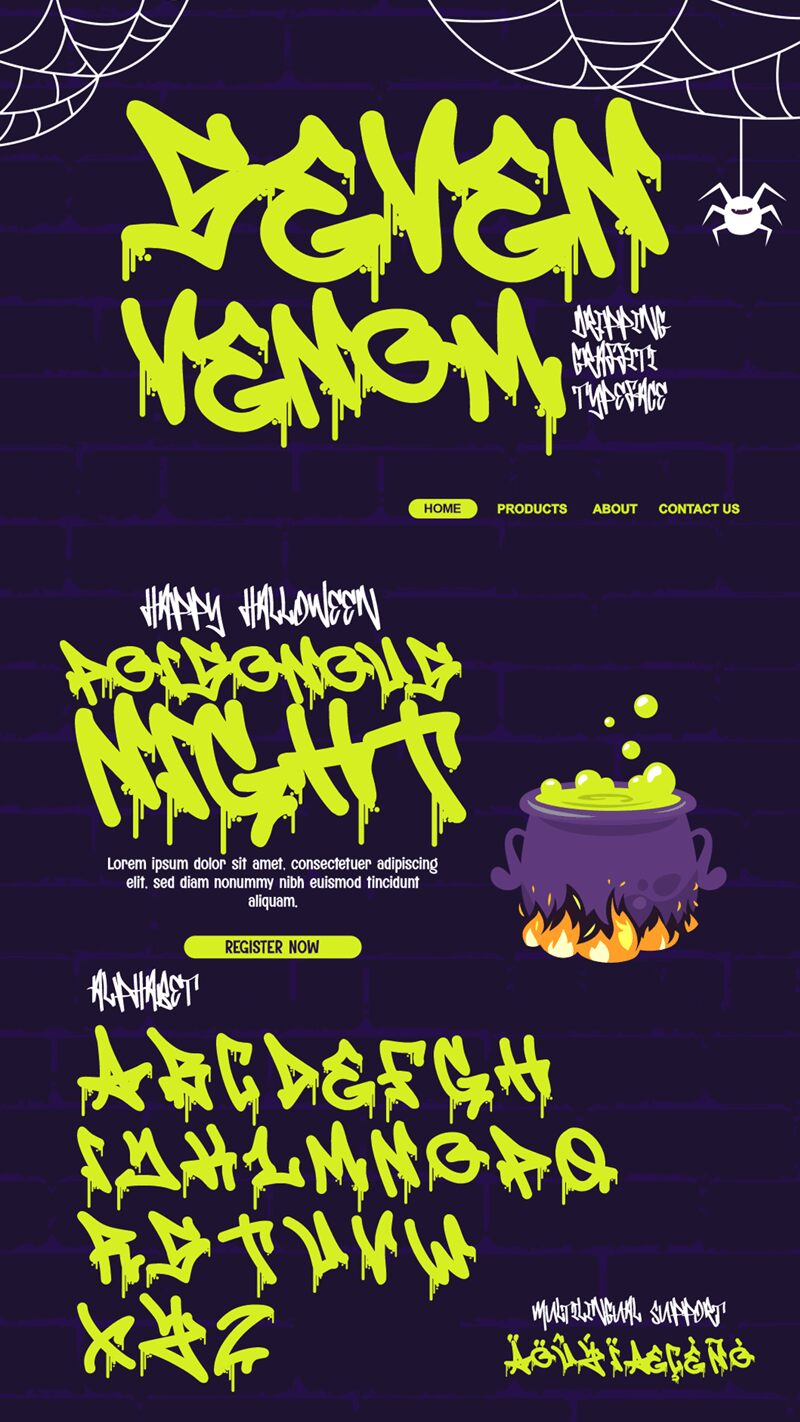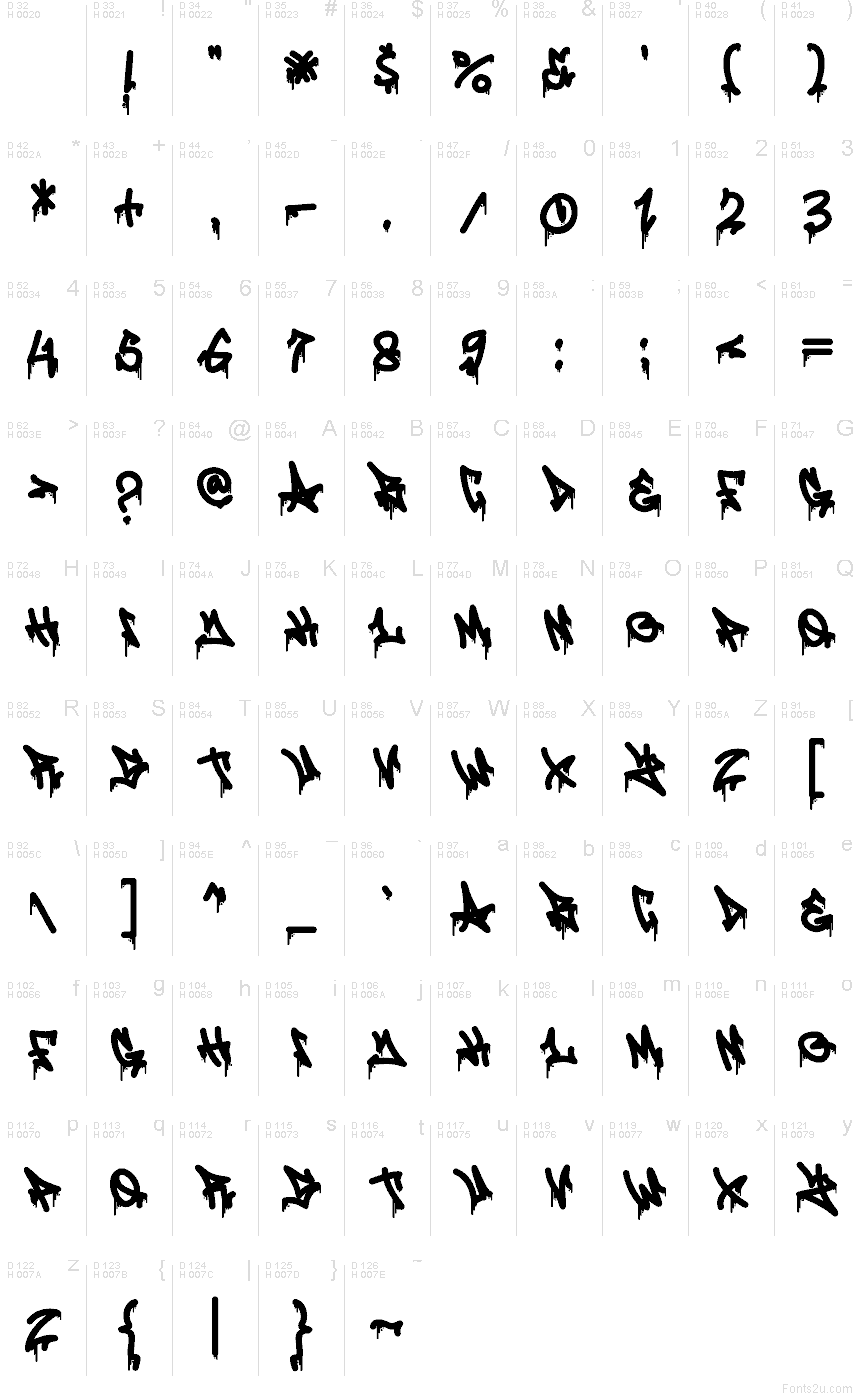
Seven Venom - Drip, font ve stylu „drip“ od Muhammada Panji Ramdhaniho z Figuree Studio, pochází z rodiny Seven Venom a je to bezplatný graffiti font. Působí jako čerstvá černá barva – špičaté tahy, roztřesený rytmus a husté kapky, které stékají s tou správnou dávkou dravosti. Rozestupy jsou záměrně nespoutané, takže i krátká slova vypadají výrazně, syrově a pouliční.
Se Seven Venom - Drip dodáte okamžitý postoj grafice na skejty a streetwear, hudebním a festivalovým plakátům, obalům alb/mixtapes, grafice na Twitch/YouTube kanály, sadám nálepek, graffiti logům a úderným sloganům na merch. Tento bezplatný font skvěle funguje v krátkých nadpisech, kde mohou kapky „dýchat“; zkuste ho použít ve velké velikosti na čistém bílém podkladu nebo betonové textuře. Pro popisky jej kombinujte s obyčejným zúženým bezpatkovým písmem, aby chaos zůstal čitelný.